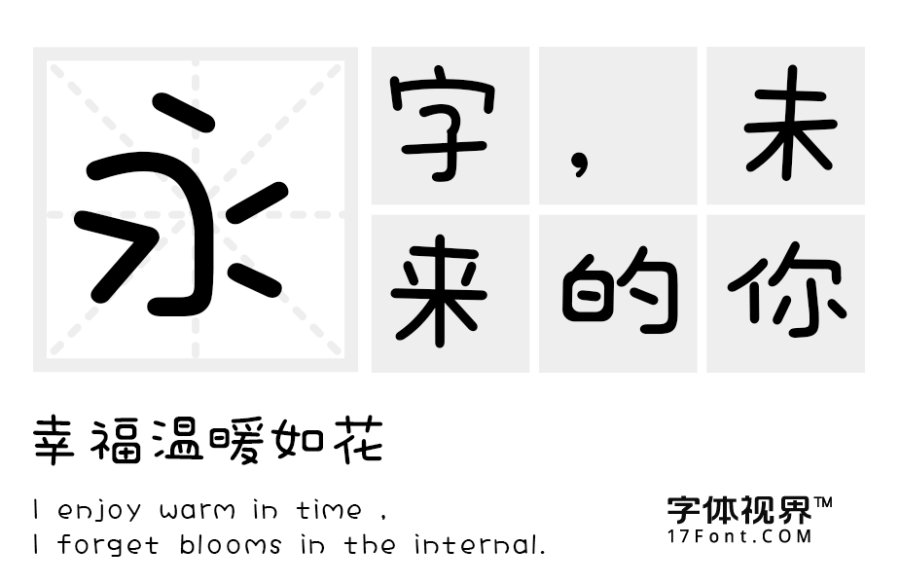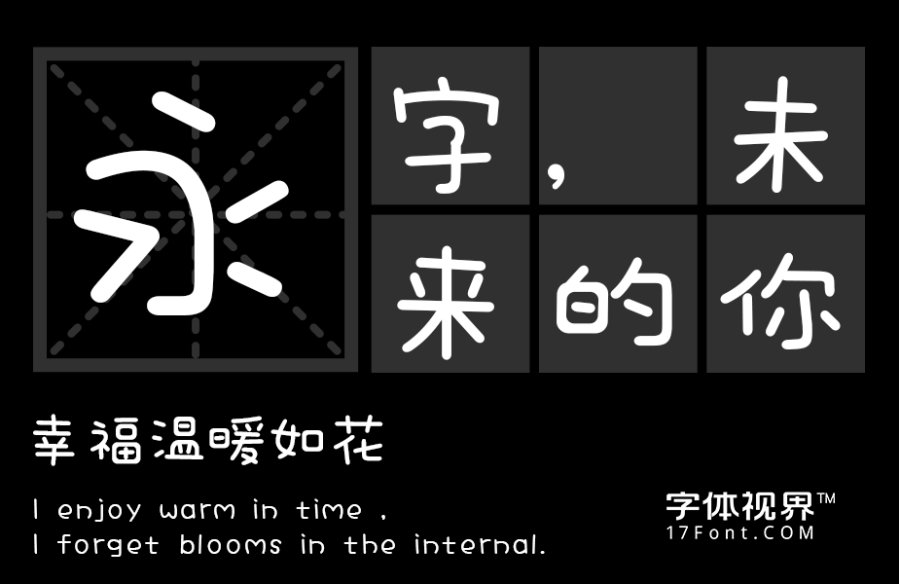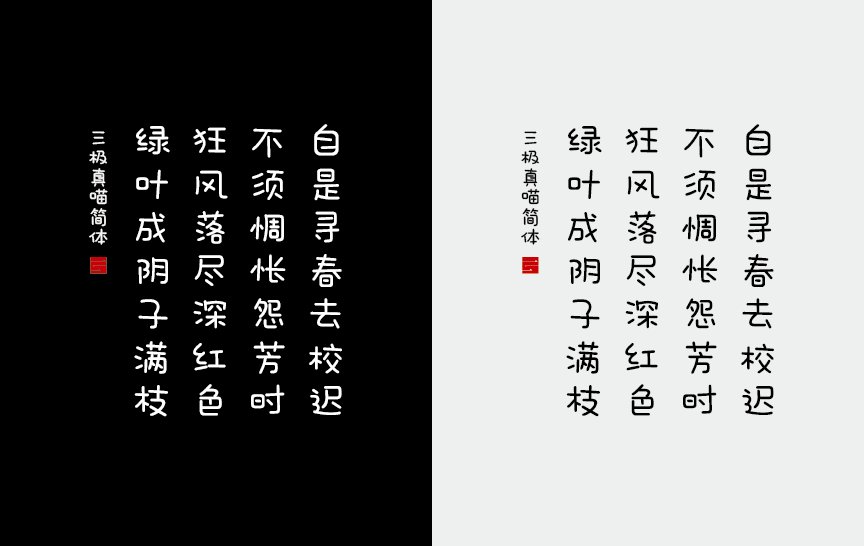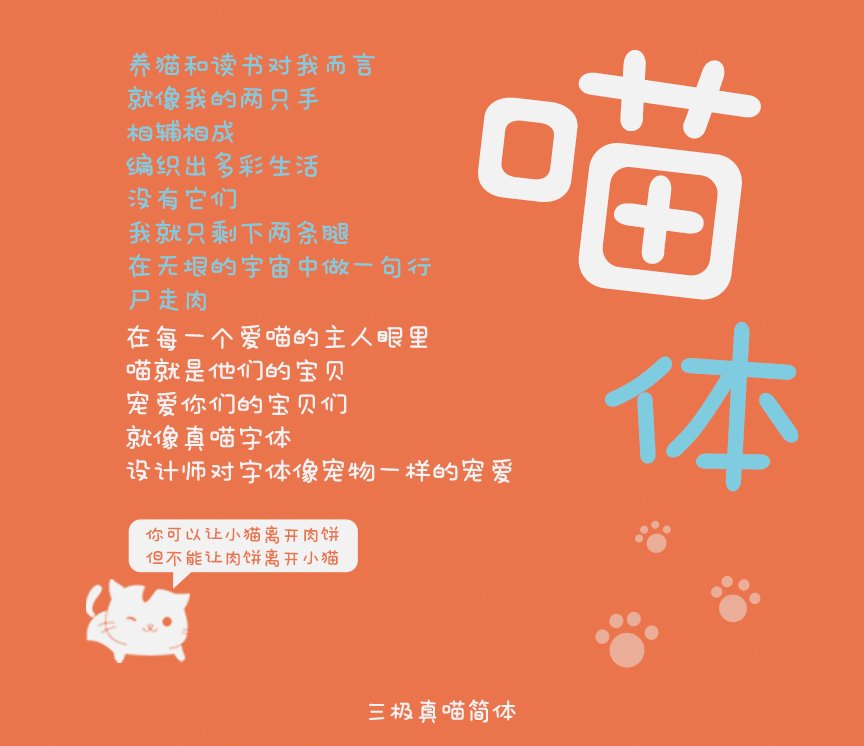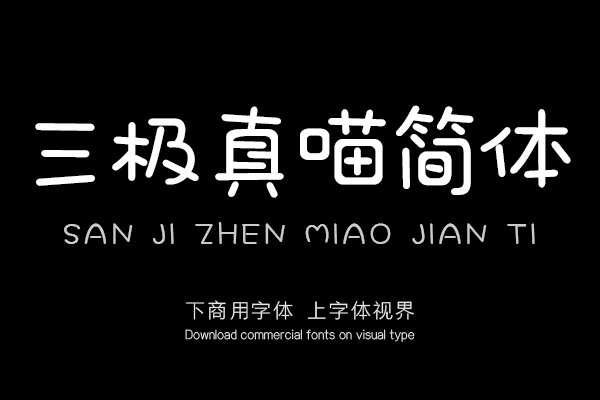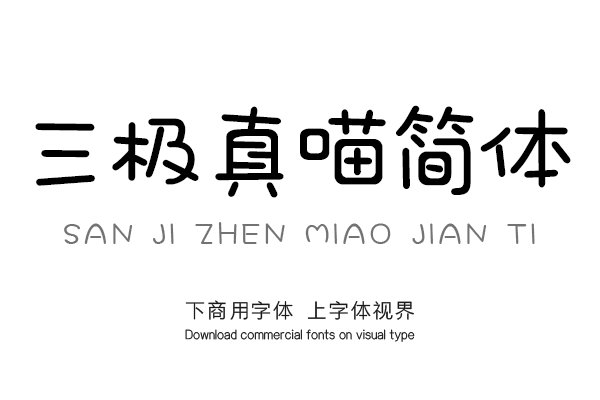
三极真喵简体用儿童写字的简拙,笔画轻松、简洁,童趣随性。字形饱满圆润,轮廓略显臃肥,整体个性明快可爱。适用于少儿类读物、书刊、品牌广告、包装设计以及社交网络个性......购买须知:“下载服务费”与“字体VIP”所获得字体 仅用于个人非商用, 商用请联系付费授权。本字体为电脑用字,手机没有root权限不支持直接手机换字(手机如何root,请自行百度搜索教程)。购买前请先 了解清楚后再付款 ,字体为虚拟产品无法回收 一旦购买不支持退款。